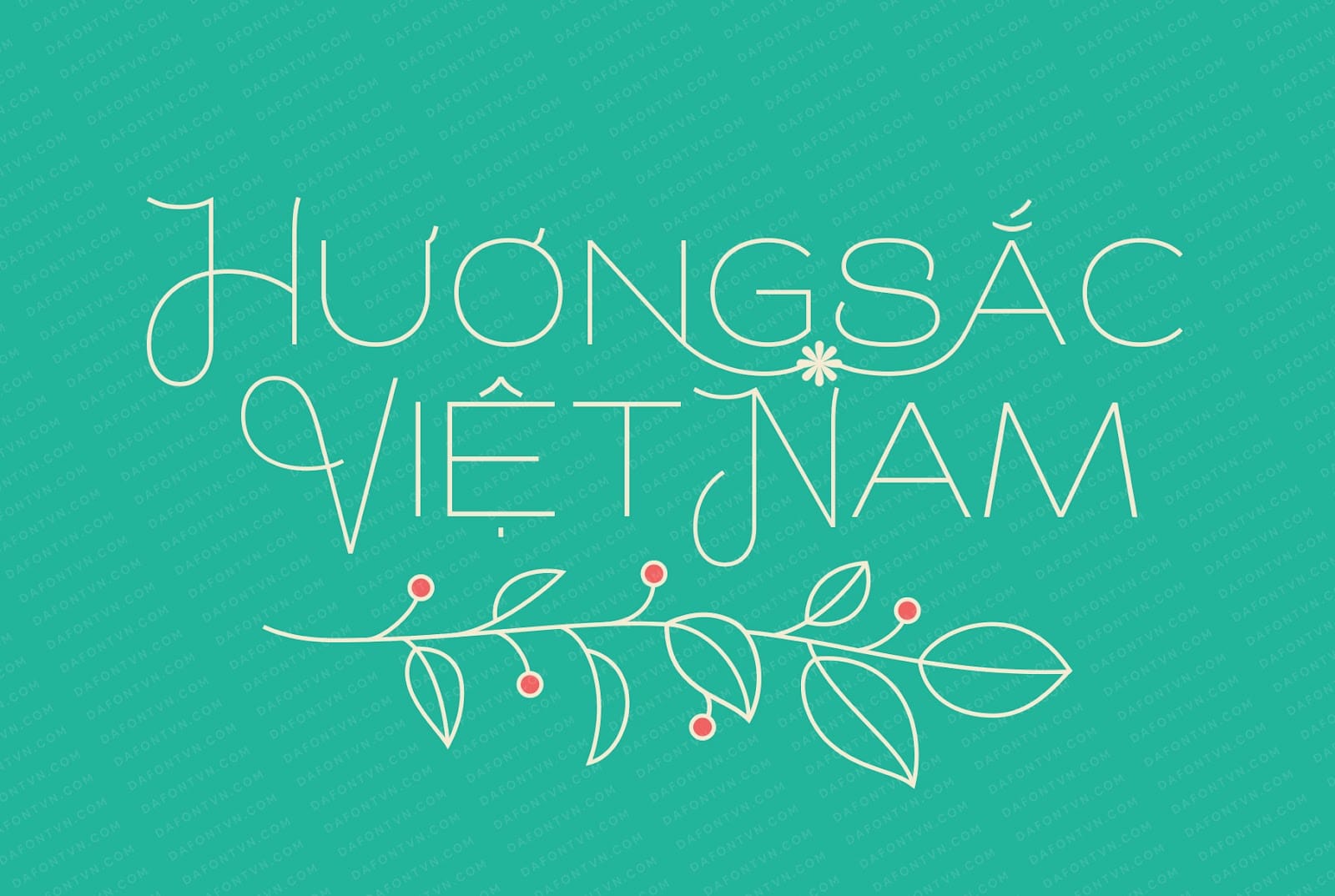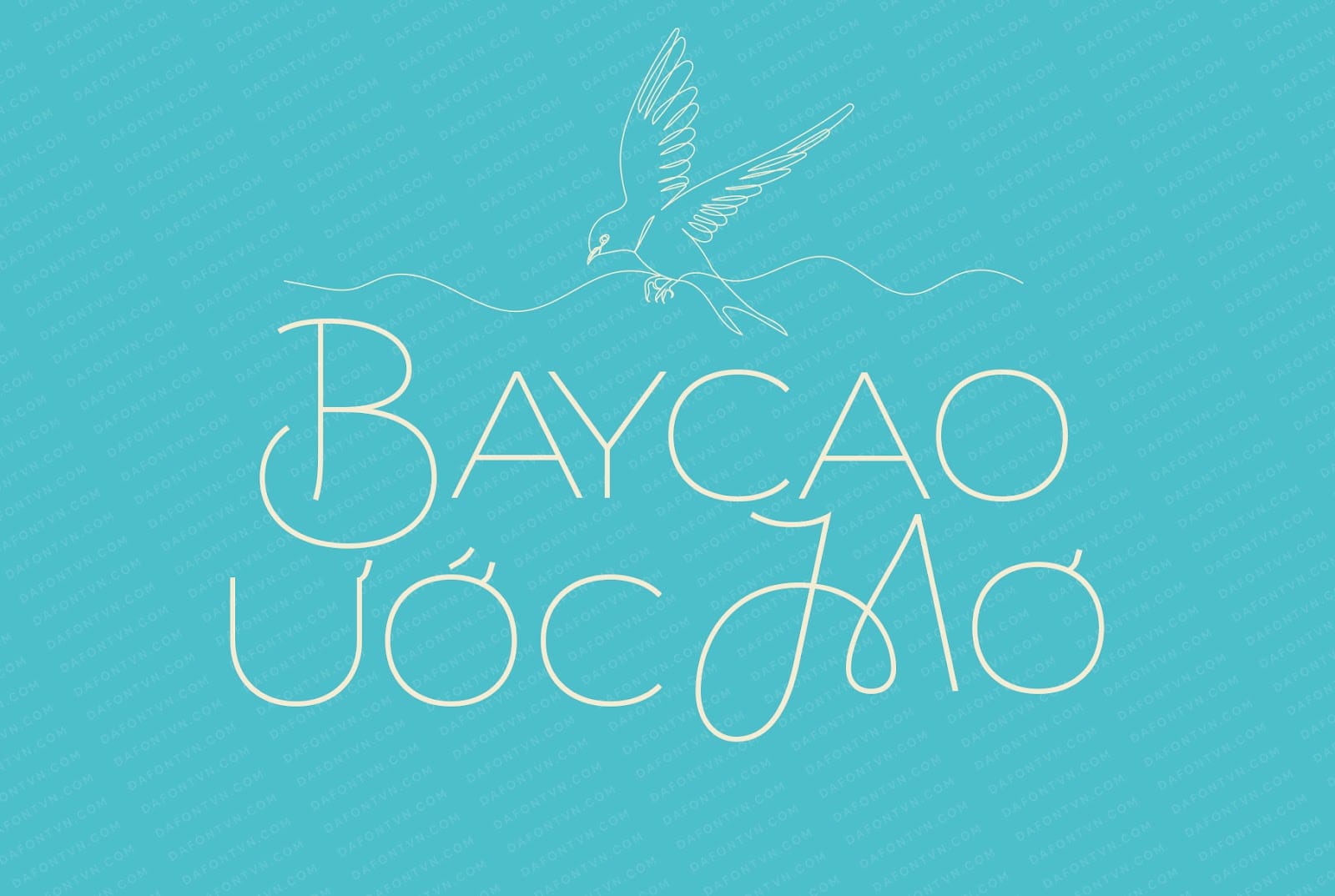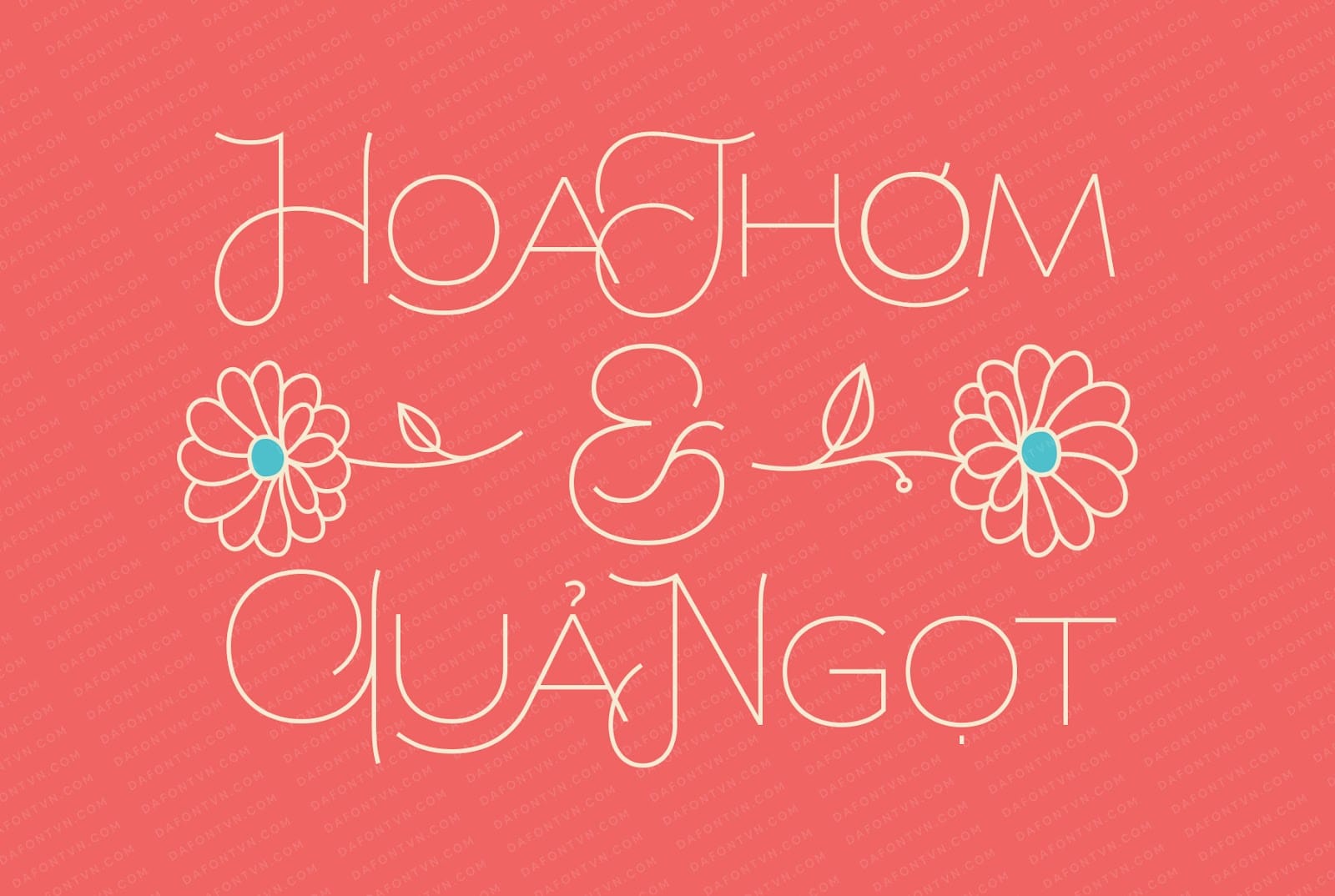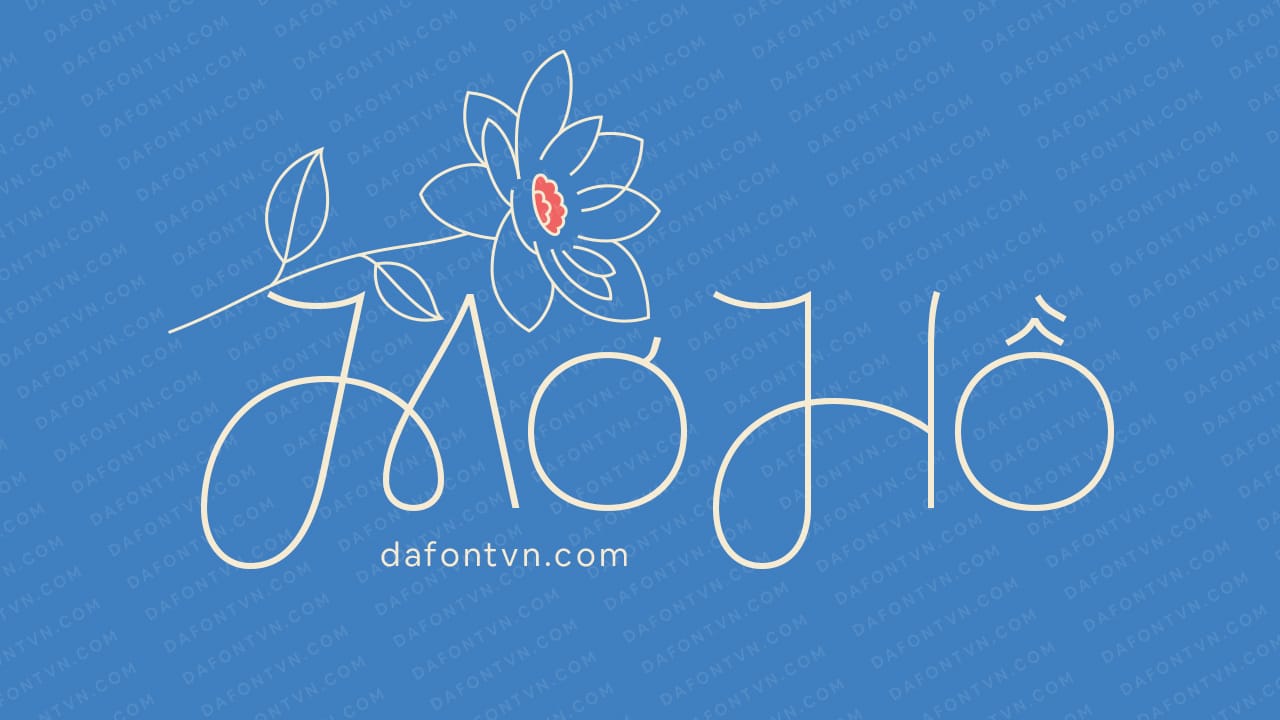
Miriam – Một font chữ thanh lịch với hình dạng nhẹ nhàng. Miriam rất phong phú về các chữ ghép (bao gồm 69 chữ ghép). Với các ký tự được thiết kế mỏng và dạng chữ viết hoa, đối với các ký tự viết hoa được thiết kế mềm mại uốn lượn đẹp mắt, các ký tự thường cứng cáp hơn. Với các nét mảnh và đường nét đẹp của nó tạo ra một lựa chọn lý tưởng cho nhiều ứng dụng khác nhau, từ giao diện kỹ thuật số đến in ấn.Điểm nổi bật của Miriam là cách tiếp cận tối giản. Các nét mảnh mang lại cho phông chữ cảm giác nhẹ nhàng và thoáng đãng. Bạn có thể sử dụng nó cho nhiều mục đích thiết kế khác nhau như xây dựng thương hiệu, logo, tạp chí, bìa sách, quảng cáo…